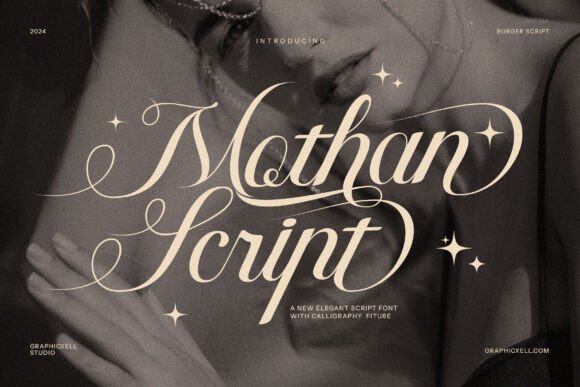
Mothan
Mothan Wedding Script Font – Review Completa e SEO‑Friendly
Mothan Wedding Script Font chegou ao mercado como a solução definitiva para quem busca elegância atemporal em projetos de design. Seja para convites de casamento, branding de luxo ou layouts digitais, esta fonte script combina traços caligráficos delicados com recursos de alternância que garantem exclusividade a cada aplicação.
Por que escolher Mothan?
- Estilo sofisticado: linhas finas e fluídas que remetem à caligrafia artesanal, perfeitas para criar convites de casamento e save‑the‑date memoráveis.
- Recursos de caracteres alternativos: mais de 30 glifos alternativos permitem combinações infinitas, evitando repetição e mantendo a identidade visual única.
- Versatilidade de uso: funciona impecavelmente em impressos (cartões de agradecimento, papelaria corporativa) e em ambientes digitais (sites, anúncios, projetos no Canva).
- Leitura e legibilidade: apesar do toque romântico, a fonte mantém boa legibilidade em tamanhos pequenos, ideal para cartões de visita e flyers.
Aplicações práticas que brilham com Mothan
- Convites de casamento: o estilo clássico eleva a primeira impressão do casal, definindo um tom de romance e luxo.
- Identidade de marca premium: logotipos, rótulos de produtos de alta gama e embalagens ganham sofisticação instantânea.
- Materiais de marketing: posters, capas de álbuns e anúncios impressos se destacam nas prateleiras e nas redes sociais.
- Web design: cabeçalhos, banners e botões de CTA em sites de eventos ou boutiques de moda ficam mais atraentes.
- Conteúdo editorial: layouts de revistas e livros de fotografia se beneficiam da elegância sutil da fonte.
Prós e contras
- Pró: alta qualidade tipográfica, vasta gama de alternâncias, excelente para projetos românticos e luxuosos.
- Contra: por ser muito elegante, pode não ser ideal para projetos que exigem um visual mais descontraído ou industrial.
Se o seu objetivo é transmitir luxo, romance e sofisticação, Mothan Wedding Script Font é a escolha certa. Seus detalhes caligráficos e recursos alternativos garantem que cada peça – seja um convite de casamento ou um logotipo de marca premium – se destaque com refinamento. Não perca a oportunidade de transformar seus projetos criativos em verdadeiras obras‑de‑arte tipográficas.